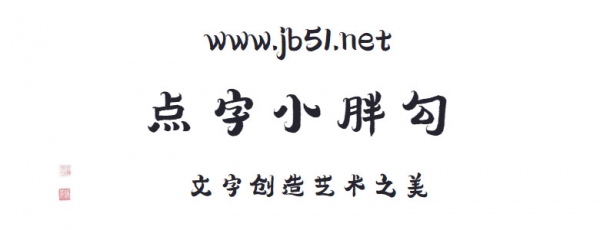
點(diǎn)字小胖勾是由點(diǎn)字庫(kù)推出的藝術(shù)字體,字形整體圓潤(rùn),在線條處理上有由粗厚入細(xì)勾,也有由細(xì)勾轉(zhuǎn)粗厚,且一筆連成,保證了字形結(jié)構(gòu)的流暢性和敦實(shí)感,,適合應(yīng)用于藝術(shù)設(shè)計(jì)、各類(lèi)廣告和產(chǎn)品包裝設(shè)計(jì)等領(lǐng)域。
該書(shū)體為全系列手寫(xiě),極大保留文字輪廓的自然與隨性。字形整體圓潤(rùn),在線條處理上有由粗厚入細(xì)勾,也有由細(xì)勾轉(zhuǎn)粗厚,且一筆連成,保證了字形結(jié)構(gòu)的流暢性和敦實(shí)感,故為“小胖勾”。 該字體給人以務(wù)實(shí)、敦厚的性格,同時(shí)也不失在豐滿中略帶俏皮感,其動(dòng)中有靜,動(dòng)靜結(jié)合。特別適用于標(biāo)題、文案、logo等多元場(chǎng)景。